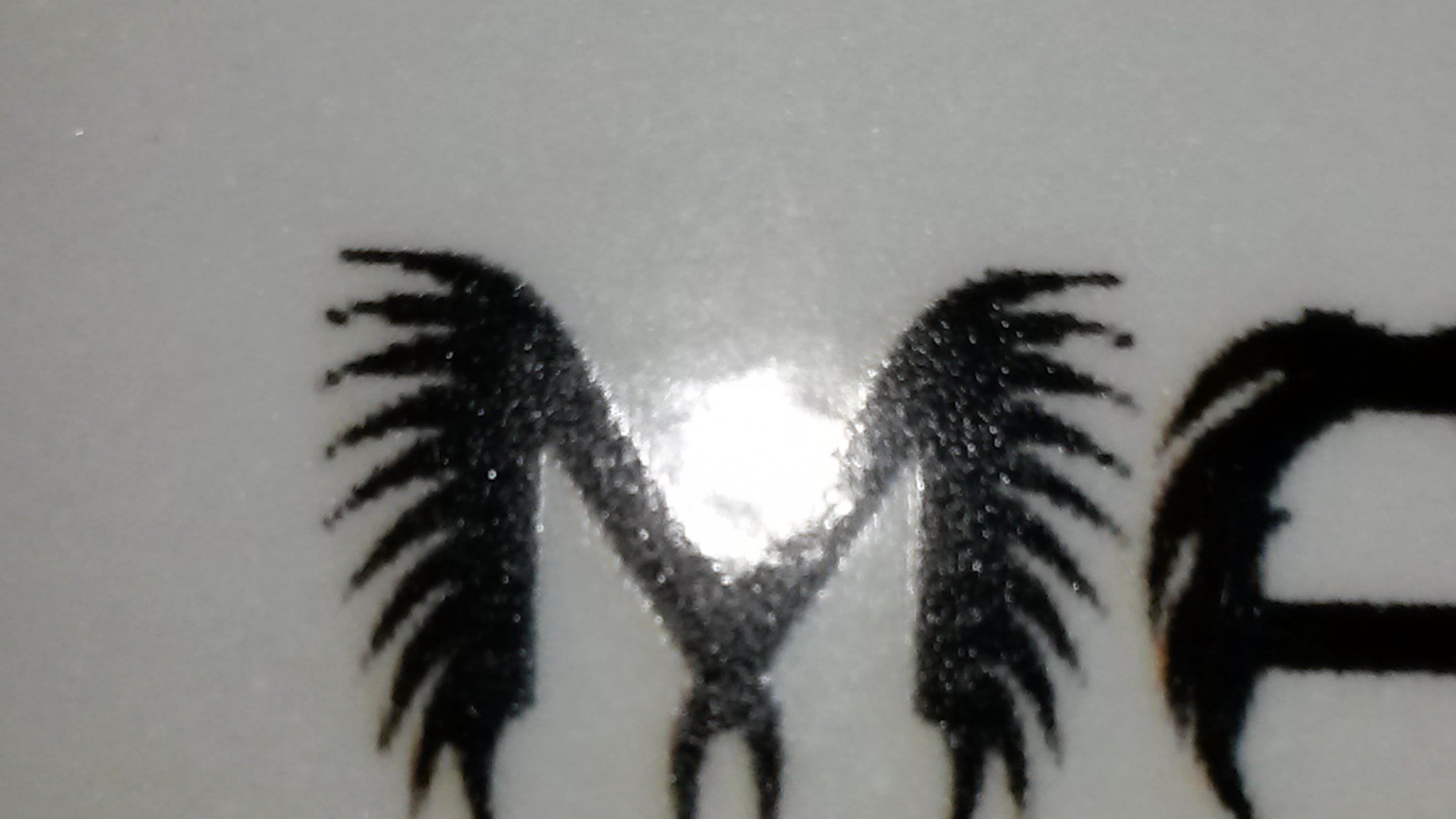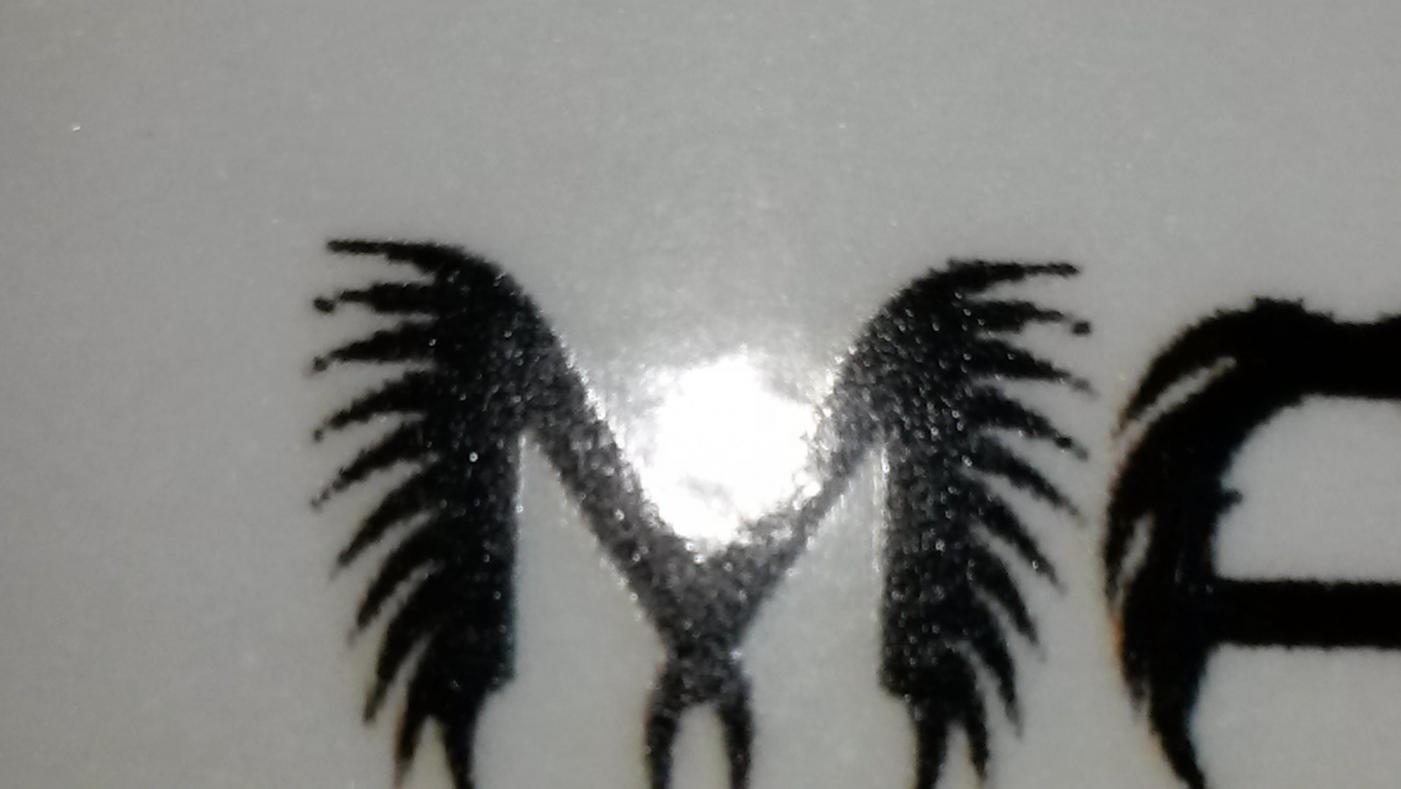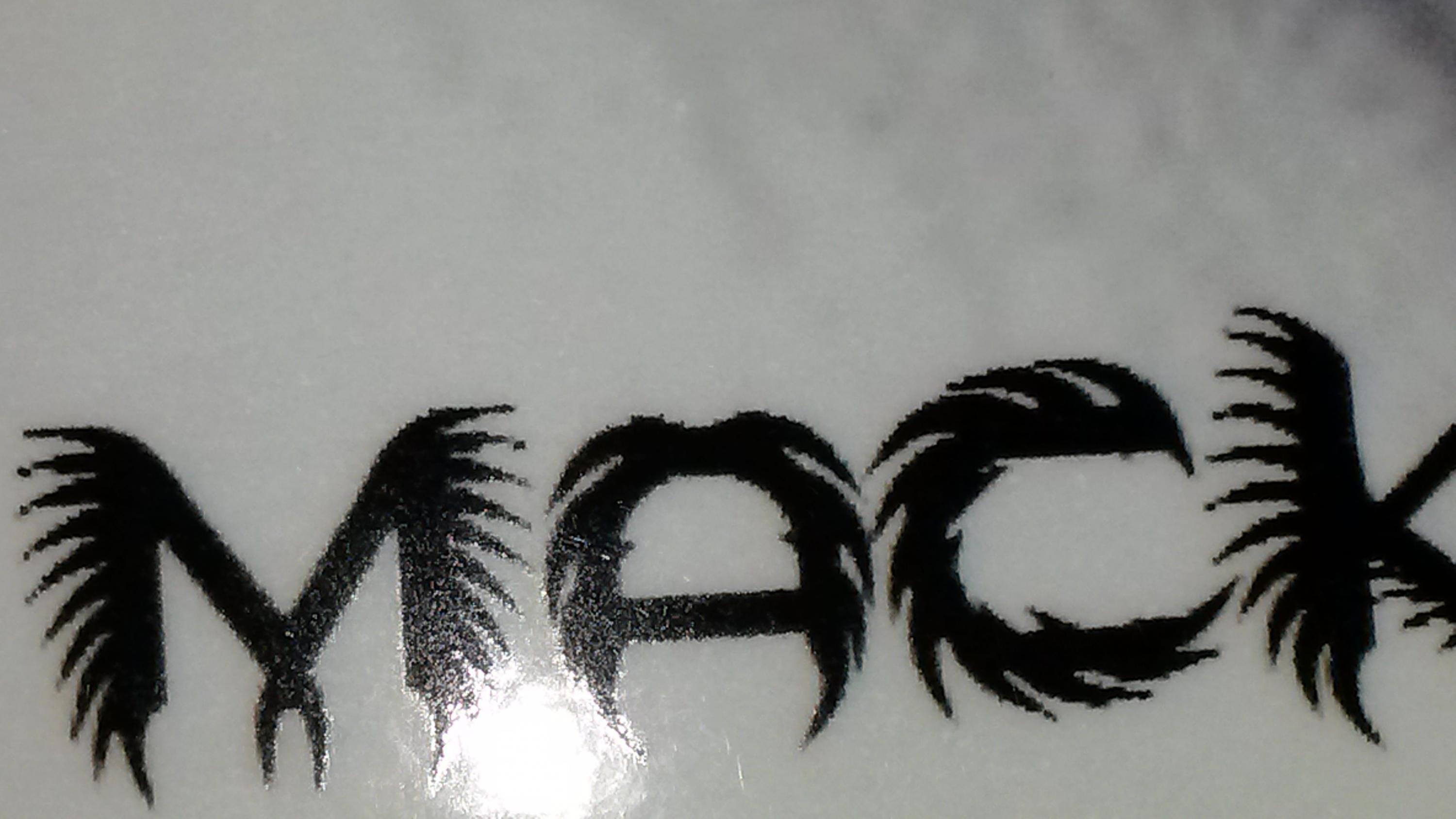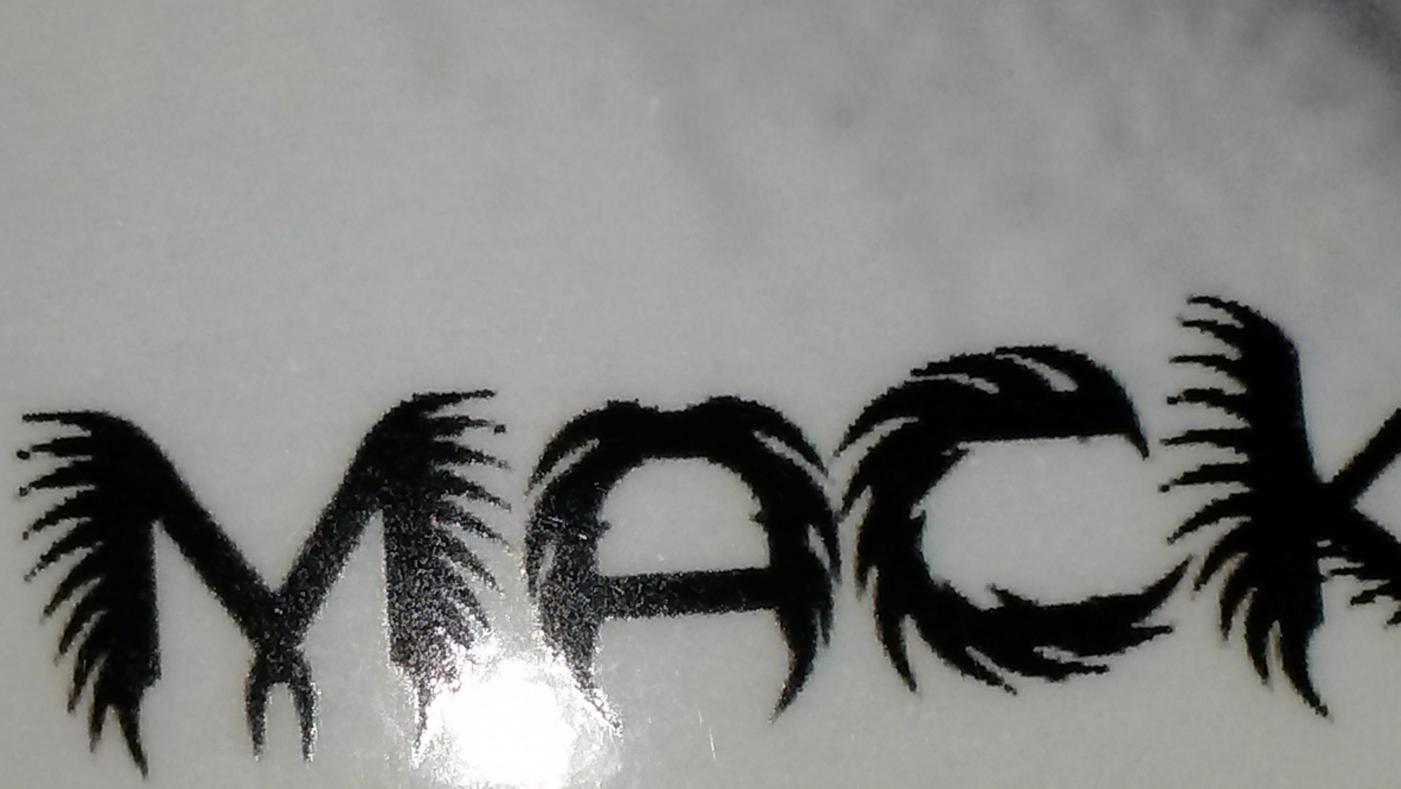
Neuer Computer, alles weg. GDI ist das einzige
durch einen Umzug ist alles weg.
Ich habe damals die Schriftart gesucht,  Tagelang. Kann mich aber nicht mehr an den vollständigen Namen erinnern, ich hoffe Ihr könnt mir da weiterhelfen. Ich meine mich zu erinnern, das ein Teil des Names GDI war.......
Leider ist auch nur ein unscharfen Druck als Muster geblieben, die Buchstaben sehen aus wie mit Federn gelegt, also um einiges feiner detailliert als auf den Fotos zu sehen.